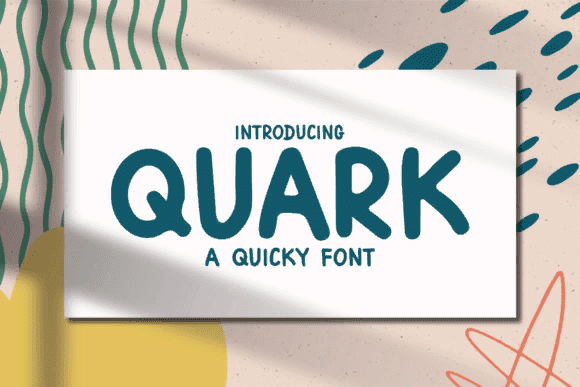
Название: Quark Font (2021)
Quark - это простой, причудливый и легко адаптируемый шрифт.
Если вы используете его для дизайна, связанного с мультфильмами, детскими играми или просто для любого творения, требующего милого прикосновения, этот шрифт станет отличным выбором.